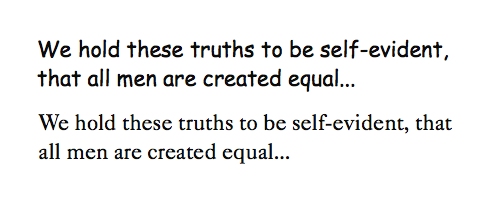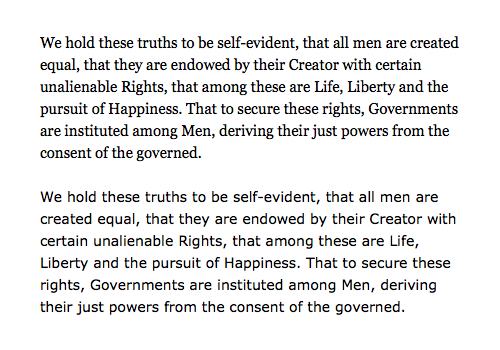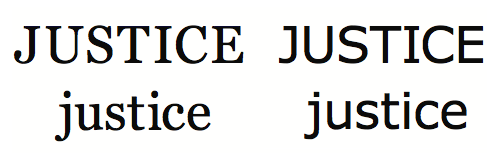
[quote]Web safe font[/quote]
Các font được sử dụng trên một website đều có nguồn gốc từ thư viện font trên máy tính của người dùng. Web safe font là những font an toàn, bởi vì hầu như chắc chắn rằng người dùng đã có những font chữ mặc định này trong thư viện. Để đảm bảo rằng website của bạn không trở lại với font mặc định (thường là Times New Roman), bạn cần phải sử dụng một web safe font.
Thật ra thì không có quá nhiều web safe font để chúng ta sử dụng
- Georgia
- Verdana
- Times New Roman
- Arial
- Trebuchet MS
- Impact
- Courier
- Comic Sans MS
Một typographer giỏi có thể sử dụng những web safe font giống nhau nhiều lần và làm cho chúng hoạt động mọi lúc. Việc sử dụng một thư viện font vượt quá các web safe font là không thực sự cần thiết.
Bạn sẽ sử dụng các web safe font trong rất nhiều bài học
[quote]Web fonts[/quote]
Web fonts là những font được lưu trong định dạng của một website. Chúng có thể được truy cập từ một máy chủ thông qua việc khai báo @font-page (bạn sẽ được tìm hiểu thêm ở phần sau)
Hãy chú ý, không phải mọi font đều được thiết kế để đọc trên màn hình. Không phải font nào cũng thích hợp cho mọi website. Không phải chỉ vì được lưu vào định dạng của một website để sử dụng cho @font-page mà nó được xem là một font tốt và hợp lý.
Web fonts bao gồm 2 loại
[quote]Self Serve[/quote]
Sử dụng khai báo @font-page, bạn có thể lưu web fonts trên máy chủ của mình hoặc của khách hàng, và trực tiếp sử dụng nó cho website.
[quote]web fonts providers[/quote]
Nếu bạn không muốn sử dụng khai báo @font-page, bạn có thể làm việc với web fonts providers. Họ sử dụng web fonts trên máy chủ của mình, và quan tâm đến khai báo @font-page ở hậu trường.
[quote]Yếu tố thẩm mỹ và cảm xúc của font chữ[/quote]
Mỗi từ đều có nội dung (denatation) và ý nghĩa (conotation). Font có thể hòa hợp cả hai yếu tố này.
Font cũng như quần áo. Chúng ta mặc nó nhưng thường không chú ý đến chúng chỉ trừ khi chúng thật sự “tuyệt” hoặc “tệ”. Đôi khi “tệ” lại liên quan đến tính rõ ràng ( khó có thể nhận ra các chữ cái). Hoặc nó liên quan đến việc nhận ra font không khớp về mặt cảm xúc và thẩm mỹ với ý nghĩa của các từ ngữ trong văn bản.
[quote]Chọn font có tính liên kết thẩm mỹ hoặc cảm xúc thích hợp[/quote]
Những liên kết cảm xúc và thẩm mỹ mà người đọc tìm thấy được trong các font đều là những mong đợi giao tiếp xã hội thường ngày. Người đọc mong đợi một tấm thiệp cưới sử dụng font viết tay cũng như họ biết cách chọn trang phục cho những dịp quan trọng như vậy. Thật ra không có một font nào có thể hoàn toàn phù hợp với cảm xúc của văn bản. Ví dụ như bạn không nên tìm kiếm một font bao gồm những trái tim hoặc cái búa trong đó. Hãy chọn một font không làm mất đi sự tập trung của người đọc vào văn bản của mình.
Mỗi từ ngữ bản thân nó đã truyền đạt một thông điệp, font chỉ là công cụ hỗ trợ. Trong Figure 1, Comic Sans trông giống như những gì mà nó thể hiện: một font không trang trọng được thiết kế để mô phỏng truyện tranh. Nó không thích hợp cho Terms & Privacy. Caslon 540 là một ví dụ của các font (của William Caslon) được sử dụng để in những văn kiện trang trọng của Tuyên Ngôn Độc Lập vào tối ngày 04 tháng 7 năm 1776. Caslon 540 có vẻ thích hợp hơn mặc dù mọi người không nhận ra nó hoặc biết đến lịch sử của nó. Những kết nối lịch sử và văn chương khác không cần thiết để người đọc hình thành nên các liên kết giữa font và văn bản.
Tuy nhiên, cuối cùng Caslon 540 vẫn không phải là một font thích hợp bất kể những liên kết lịch sử của nó. Để đánh giá mức độ rõ ràng sang một bên, Caslon 540 không phải là web safe fonts.
[quote]Sử dụng Font serifs truyền thống và Sans Font serifs hiện đại[/quote]
Chúng ta tạo nên những liên kết cảm xúc giữa font serifs và sans font serifs, chịu ảnh hưởng bởi các chữ cái và font đã được sử dụng hàng trăm năm nay.
Chữ serif là một phần của cảnh quan văn hóa ít nhất là từ thế kỉ thứ nhất trong các chữ khắc, văn bản viết tay và font. Các chữ serif trên Trajan’s Column ở Rome ban đầu được khắc trên đá trước khi đập ra và sơn lại. Các tài liệu viết tay không trang trọng vào thời đó đều sử dụng chữ thảo, nhưng các văn bản trang trọng và bản thảo được viết trong Latin Book Hand. Mặt chữ serif thành công đầu tiên được cắt giảm vào năm 1470 bởi Nicholas Jenson. Do vậy, nhiều thế kỉ sau, sách và các tài liệu in trang trọng đều sử dụng font serif. Chữ serif luôn mang một giá trị cổ xưa và quan trọng trong cuộc sống chúng tôi.
Như vậy, chữ sans serif đứng sau chữ serif cho đến khi Thế chiến thứ nhất kết thúc. Trong những năm 1920, sau nhiều năm sống ở đất nước chịu sự tàn phá của chiến tranh, một nhóm các nhà thiết kế người Đức – the Modernist – một phát triển một hướng đi mới nhằm giúp xã hội thịnh vượng hơn. Chịu ảnh hưởng của quá trình công nghiệp hóa, The Modernist đề cao tính rõ ràng hơn cả vẻ đẹp. Họ đã nhìn thấy các công trình trang trí không cần thiết, bao gồm cả font serif trong letterforms, và họ buộc tội Thuyết truyền thống của cuộc sống trong quá khứ đã bắt chước những gì trước đó.
Vì lí do nghệ thuật và kinh tế, Thuyết truyền thống và thuyết hiện đại đều bảo vệ lý thuyết của riêng mình. Và cuối cùng, mỗi kiểu chữ vẫn tiếp tục hiệu quả trong những lịch vực riêng. Chủ nghĩa truyền thống thành công với thiết kế sách, trong khi chủ nghĩa hiện đại chiếm ưu thế với không gian số.
Định dạng
Ý nghĩa không chỉ thể hiện qua font. Khi bạn sử dụng một đơn vị nhỏ trong văn bản (như một từ, câu nói, tiêu đề…) nó giúp xem xét cách người đọc hiểu ý nghĩa của các chữ in thường, in nghiêng, in hoa.
Tất cả đều viết hoa
Viết hoa tất cả các chữ cái biểu thị sự quan trọng, quyền lực, đáng tin cậy và sự bền vững. Các chữ cái sẽ lớn hơn và đòi hỏi khắt khe hơn. Các chữ cái có xu hướng hình vuông, ít biến đổi hình dạng và giảm bớt các kiểu hình tròn. Bảng chữ cái đầu tiên của La Mã và Hy Lạp không có chữ thường, vì vậy tất cả các chữ cái trong bản khắc dưới đây đều ở dạng chữ in hoa. Vì chỉ có những câu nói và ý tưởng quan trọng được khắc trên đá, người ta bắt đầu cho rằng chữ in hoa tượng trưng cho quyền lực và sự quan trọng.
Tất cả đều viết thường
Điều này mang đến cảm giác thân thiện, không quá trang trọng. Những biến thể trong hình thức, hình dạng tròn và cảm giác đàm thoại thông thường.
Chữ in nghiêng
Font này nhìn giống như chữ viết tay nên sẽ tạo nên cảm giác nhân văn cho người xem. Các chữ cái thường kết thúc bằng đường cong, các nét thanh và đậm gợi nhớ đến bút và mực được sử dụng để viết chữ ngày xưa.
Tuy nhiên chữ in nghiêng tuyệt đối chỉ nên sử dụng với font serif. Sử dụng font sans serif cho chữ in nghiêng sẽ tạo nên một cảm giác khô cứng và thô kệch.
Quirky Fonts
Quirky Fonts mang đến ý nghĩa bổ sung cho từ ngữ và nhắc nhở rằng chúng ta không thể phân biệt kiểu in bằng serif và sans serif. Ảnh hưởng của font sans serif rất khác so với Verdana. Tác động của các nét đậm tạo cảm giác quyền lực mạnh mẽ hơn.
Khác với Georgia, Courier không mang tính truyền thống. Nó thể hiện rằng “Xin chào, tôi đã được viết trên một máy đánh chữ”